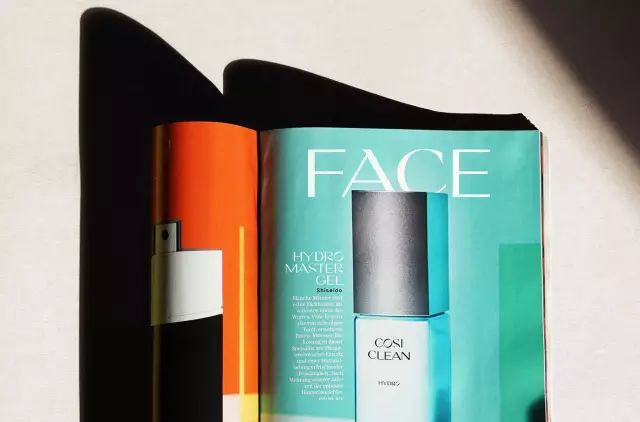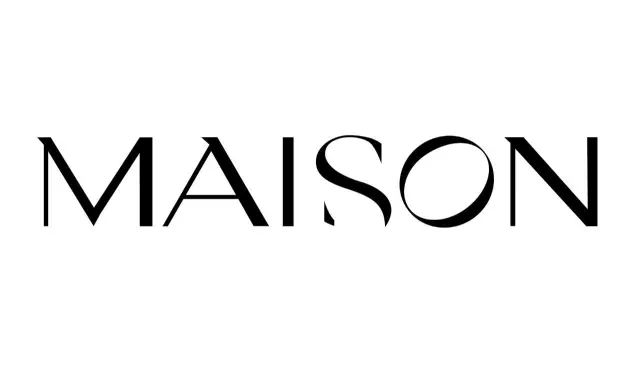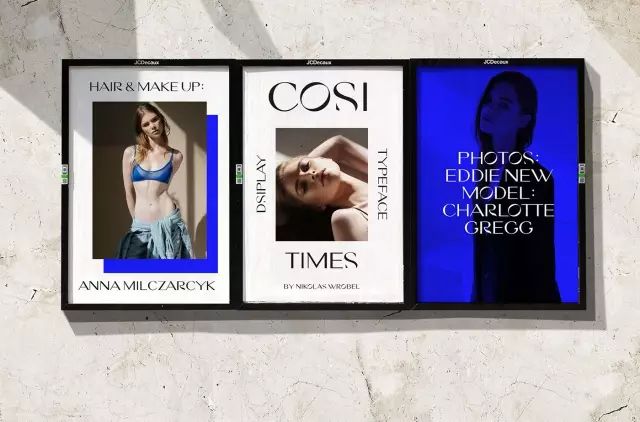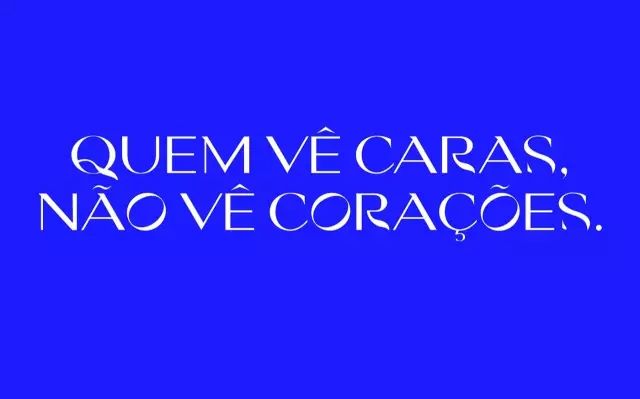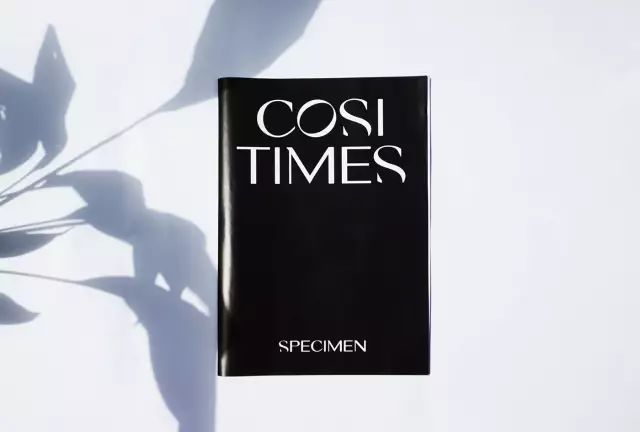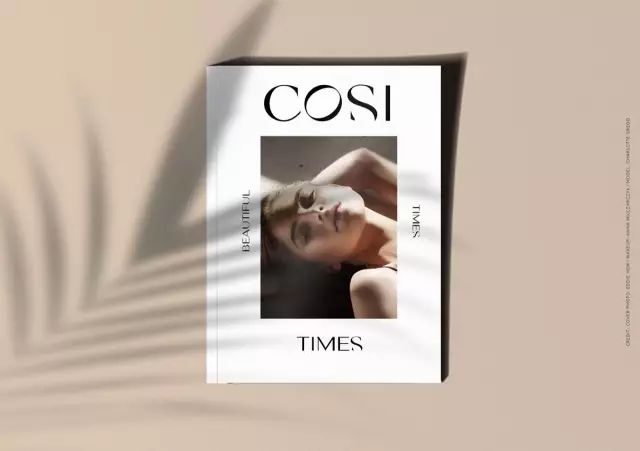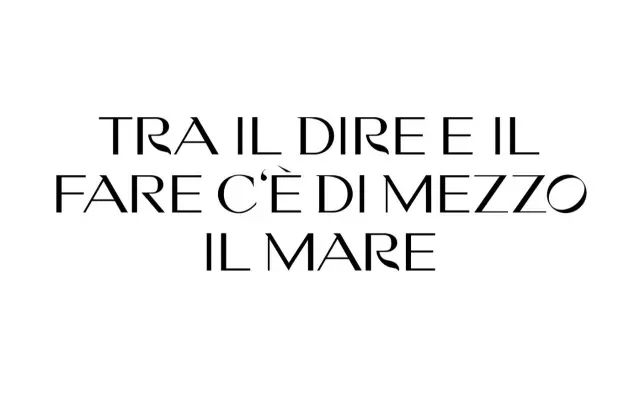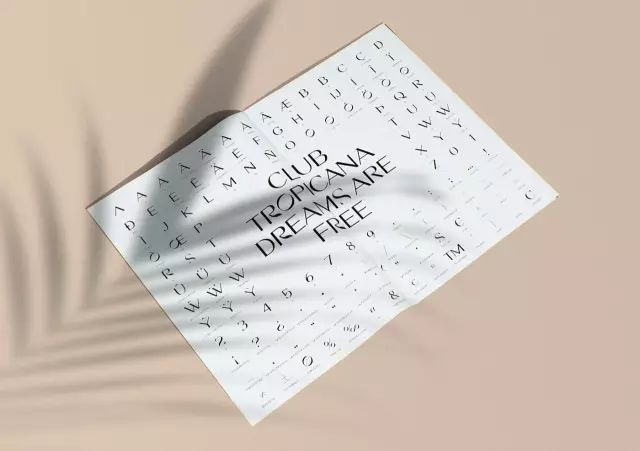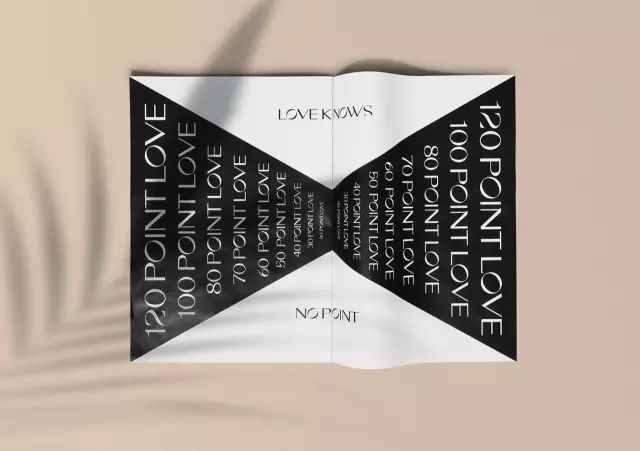
他为爱情设计了一款字体,太浪漫了~
今天和大家分享一款新字体:
Cosi Times Typeface,
来自德国设计师 NIKOLAS 的作品。
对Nikolas来说,设计不仅仅是表面的。
优秀的设计有一个普遍的“真理”:
触发表面,信息归纳,产生灵感。
这款 Cosi Times 新字体,
8月18日刚刚发布,
是庆祝他的爱情走向 Typography。
他的爱情充满着美丽、温柔和宁静的回忆,
因此将其设计成一款现代、时尚的字体。
一起看看。
152 Glyphs,一个爱,